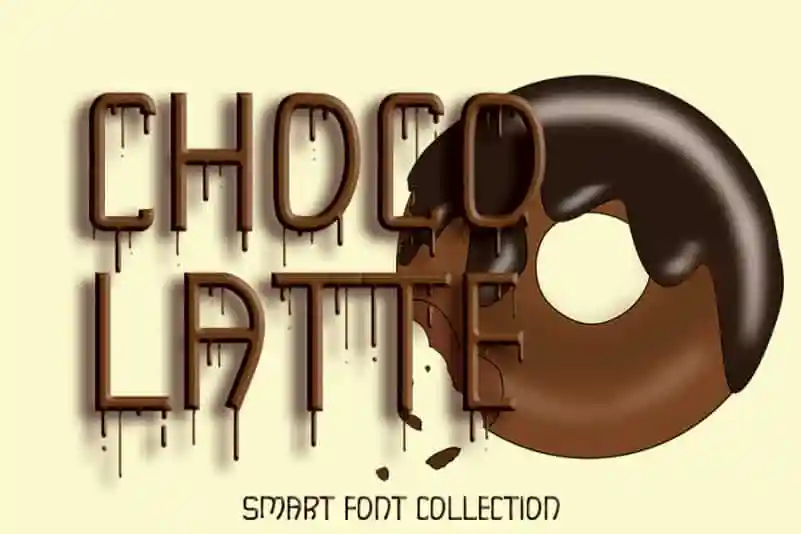
Chocolatte Display Font – Download Grátis
A Chocolatte Display Font é uma elegante escolha para quem busca brilho e modernidade em seus projetos digitais. Especialmente criada para adicionar destaque a seus trabalhos, essa fonte não apenas reforça sua personalidade única, mas também aumenta o impacto visual de seu conteúdo. Ela é ideal para gráficos publicitários, marcas, e design web que precisam soar inovadores e divertidos ao mesmo tempo. Com Chocolatte Display Font, suas idéias criativas terão um salto ainda maior em termos de visibilidade, tornando-a uma opção irresistível para quem procura um toque especial no seu próximo projeto visual.